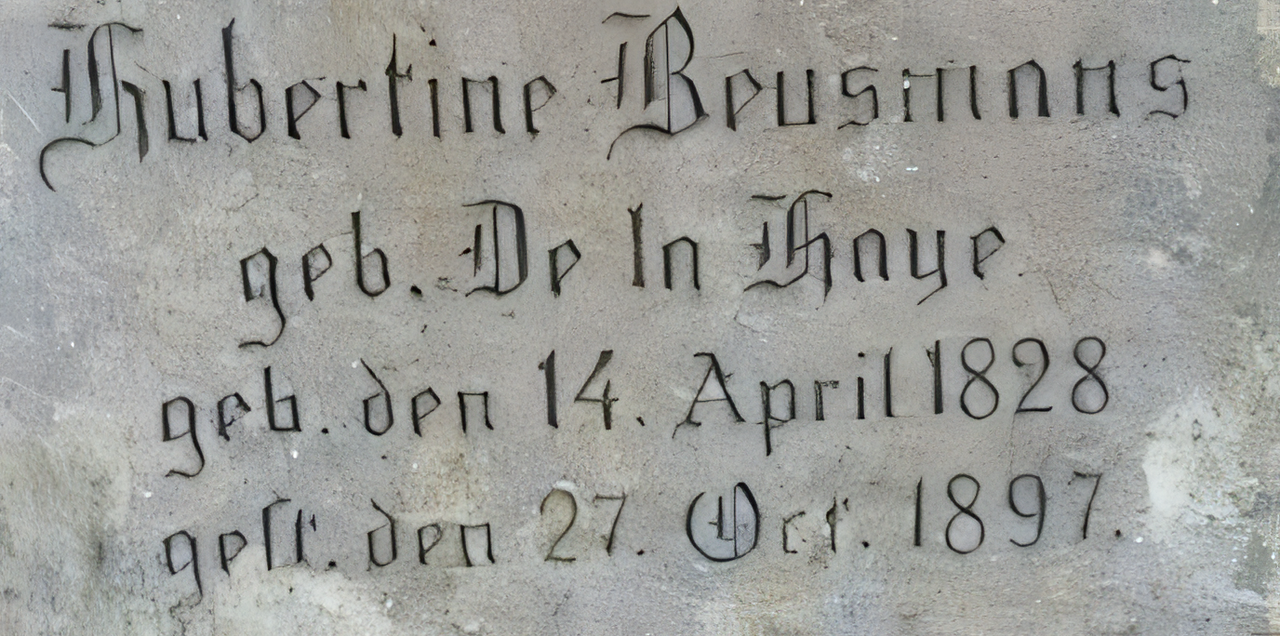
Schriftart für Grabstein gesucht um 1900
mein Stiefvater ist vor kurzem verstorben und in einem alten "Familiengrab" beigesetzt worden, in dem die letzte Bestattung 1925 erfolgt ist. Für die Urne soll jetzt eine Platte bestellt werden, die zu dem Grabstein passt, aber trotz langer Suche im Internet können weder wir noch der Steinmetz feststellen, um welche Schriftart es sich handelt. Meine Recherchen haben nur ergeben, dass es wohl eine gotische Frakturschrift ist, was mir aber nicht viel weiter hilft.
Daher möchte ich hier fragen, ob jemand eine ähnliche Schriftart kennt oder eine Idee hat, wie man eine ähnliche Schriftart bekommen könnte?
ich dachte, ich hätte die Anlage schon mit hochgeladen, aber da hat was nicht richtig funktioniert. Hier ist ein Ausschnitt der Inschrift:
die letzte Bestattung 1925
Dann wirst du grundsätzlich nur eine ähnliche Schriftart finden, da damals keine Satzschriften Grundlage waren, sondern dem Steinmetz höchstens als gedankliche Stütze für seine Handarbeit gedient haben.
basierend auf der Engraver’s Old Englisch
Ich hatte spontan wegen der feinen Linien und der Gestaltung von »m« und »n« an die Unger Fraktur gedacht (die aber stilistisch dann doch recht weit entfernt ist). Unter den Gotischen geht vielleicht die bei Herrn Helzel unter dem Namen Ihlenburg Gotisch erhältliche Schrift in die gewünschte Richtung (Formsprache der Alten Englischen kombiniert mit feinen Linien). Aber so richtig passt die auch nicht.
Ich stelle fest, das ich noch viel über Schriften zu lernen habe. 😉 wie heißen denn die dünnen Verzierungslinien in den Buchstaben?
Die wedding-Text-Schriftart hatte ich auch schon gefunden, das B ist fast identisch, aber das H passt leider nicht. Vielleicht kann der Steinmetz aber etwas damit anfangen.